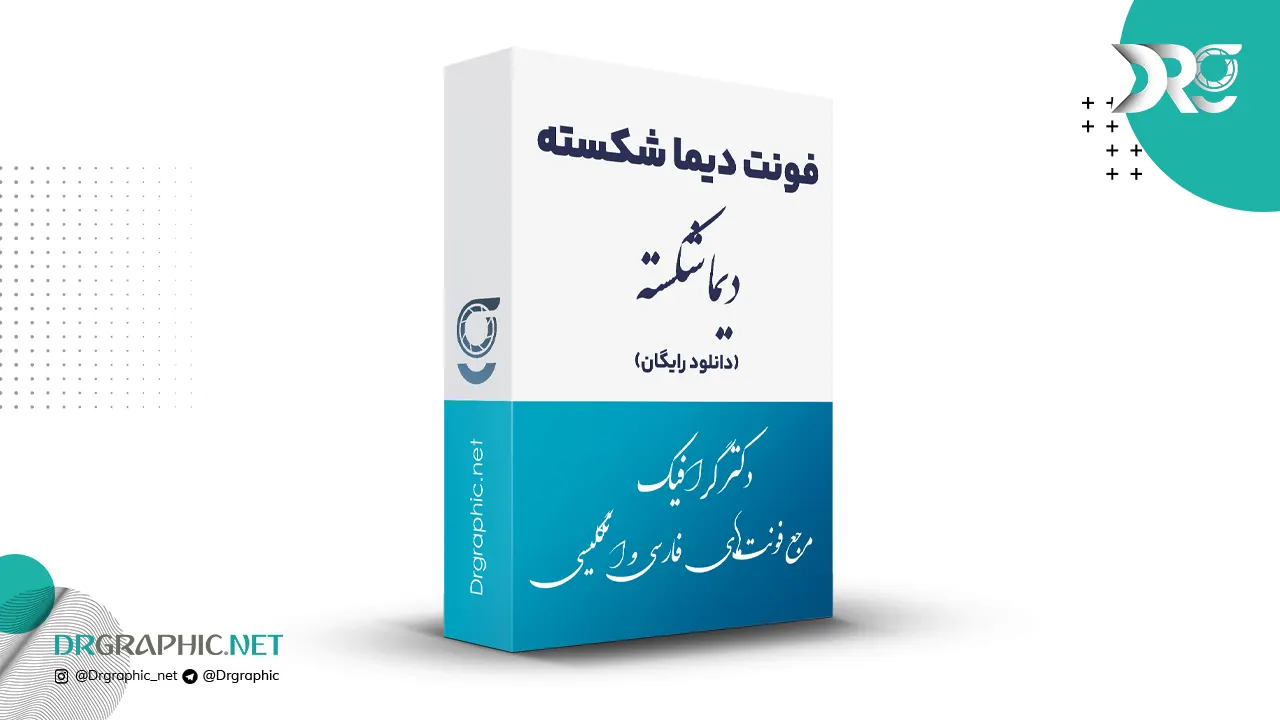
فونت دیما شکسته dima shekaste 3
• کاربرد: خوشنویسی دیجیتال، تایپ در نرم افزارهای ورد ، آفیس ، فتوشاپ ، کورل، ساخت عکس‌نوشته‌های گرافیکی و …
این فونت فارسی یکی از بهترین فونت های نستعلیق شکسته می باشد که شما می توانید در طراحی های خود استفاده کنید.
نمونه نوشته با این فونت: